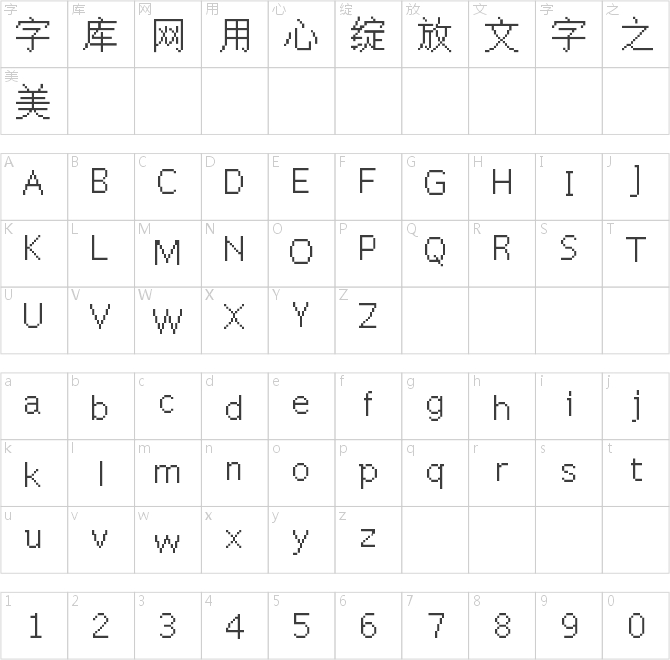
文泉驛點(diǎn)陣宋
文泉驛點(diǎn)陣宋體是一個(gè)”自由中文字體”。該字體包含了所有常用簡體中文、繁體中文,日文及韓文所需要的漢字(最新版本包含超過27842個(gè)漢字,完整覆蓋GB2312/Big5/GBK/GB18030標(biāo)準(zhǔn)字符集)。該字體同時(shí)還包含了英文、日文、韓文和其他多種語言符號(hào)。該點(diǎn)陣字體包含五個(gè)屏幕常用字號(hào)(9pt-12pt),逾21萬漢字點(diǎn)陣,這些點(diǎn)陣都經(jīng)過參與者和組織者的精心設(shè)計(jì)和調(diào)整,手工優(yōu)化后的漢字點(diǎn)陣顯示清晰銳利,特別易于屏幕閱讀使用。
此為娛樂部以文泉驛點(diǎn)陣宋體 v1.0.0-RC1 的 PCF 字體制作的 TTF 版字體。希望可以給中文的點(diǎn)陣字體和像素字體增加一個(gè)新的選擇。